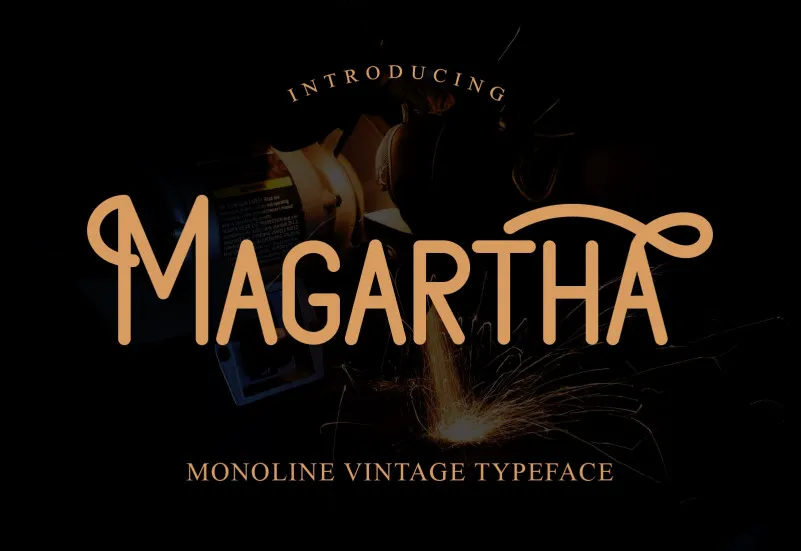
A Magartha Font é uma elegante escolha para qualquer projeto que você tenha em mente. Especificamente projetada para se encaixar com setores amplos e variados, essa fonte criada pelo designer Galatamen apresenta um visual vintage inconfundível. Com seus caracteres em caixa alta sólidos, ela oferece uma versatilidade incrivelmente ampla que pode facilmente complementar muitas ideias criativas. Seja para a tipografia de sites, design gráfico ou até mesmo o branding de sua marca, Magartha está aqui para destacá-la. Adicione-a à sua paleta e note como ela lhe auxilia a criar visuais inovadores e memoráveis.